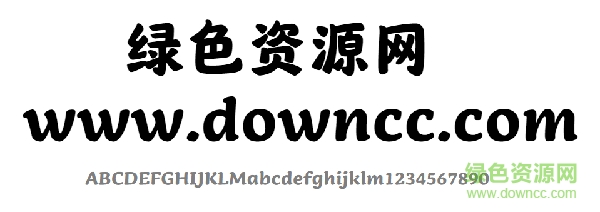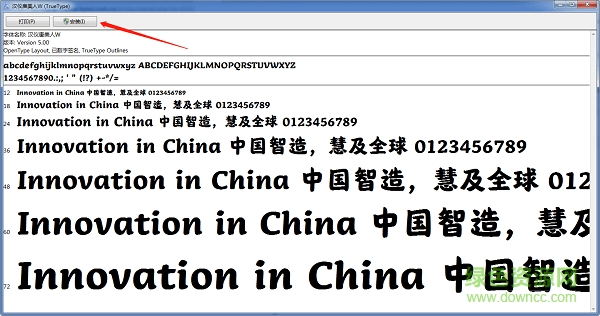
漢儀唐美人字體繁是一款極具古風(fēng)韻味的字體,渾厚的筆鋒取材于古代毛筆字,簡(jiǎn)單的明明了的游戲字體形態(tài)讓整個(gè)書面看起來更加的舒適,此款字體無論是使用于標(biāo)題上還是其他的地方都是不錯(cuò)的,喜歡就來綠色資源網(wǎng)下載吧!
漢儀唐美人W字體是一款十分不錯(cuò)的中文簡(jiǎn)體字體,這款字體筆觸較為粗實(shí),字體清晰且明朗,適合應(yīng)用于藝術(shù)設(shè)計(jì)、平面宣傳設(shè)計(jì)、網(wǎng)頁設(shè)計(jì),書法字帖等領(lǐng)域,需要的朋友不妨前來本站下載使用!